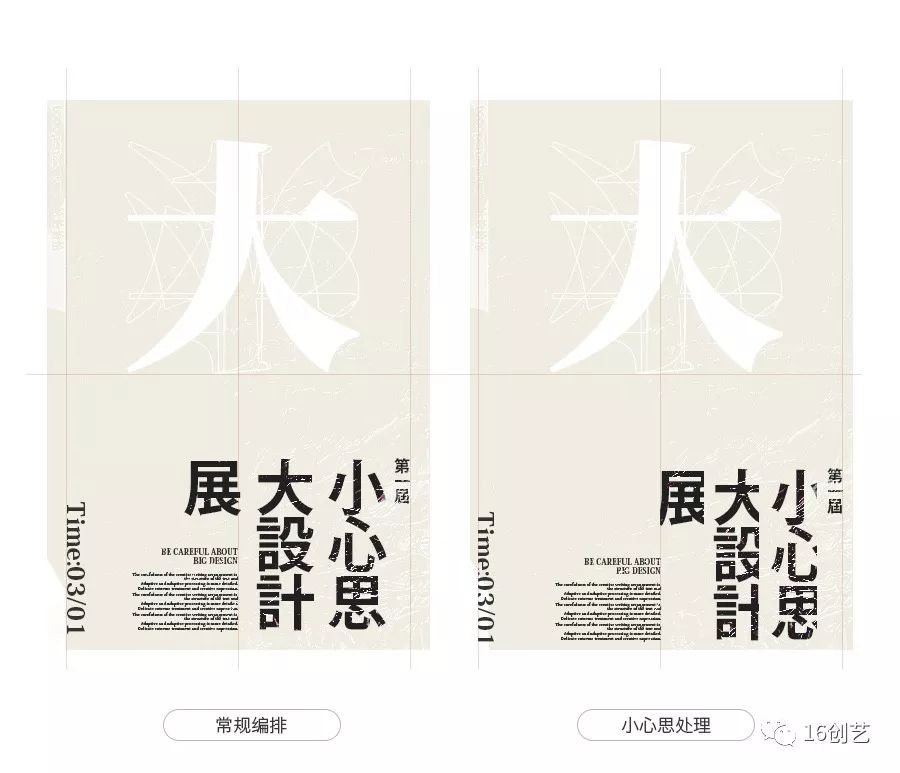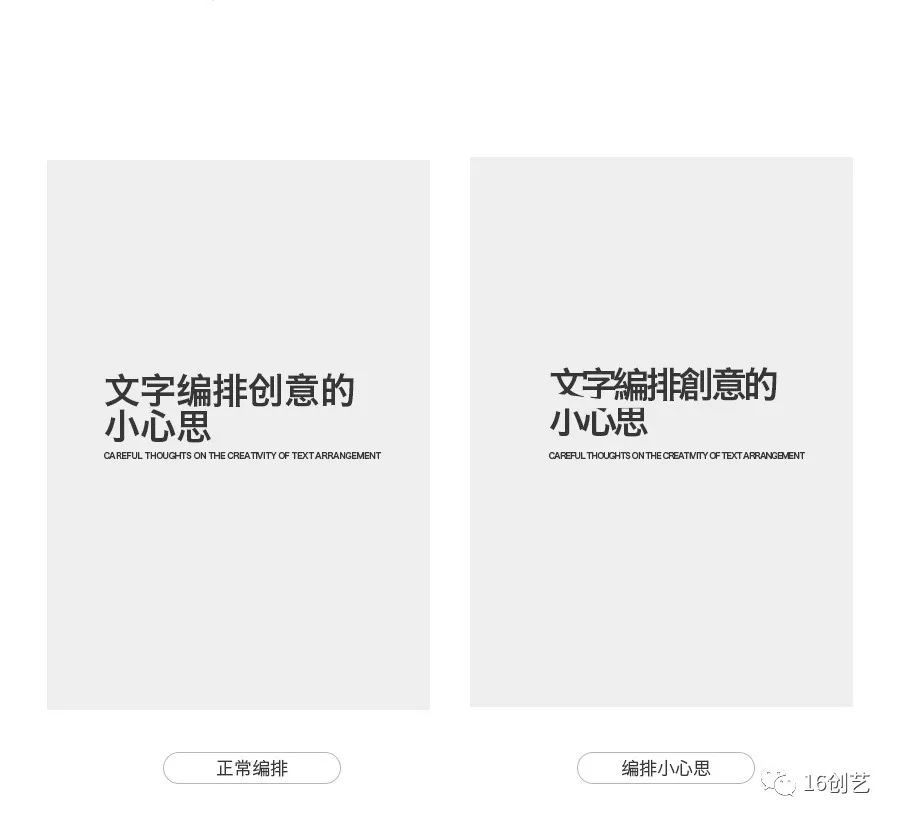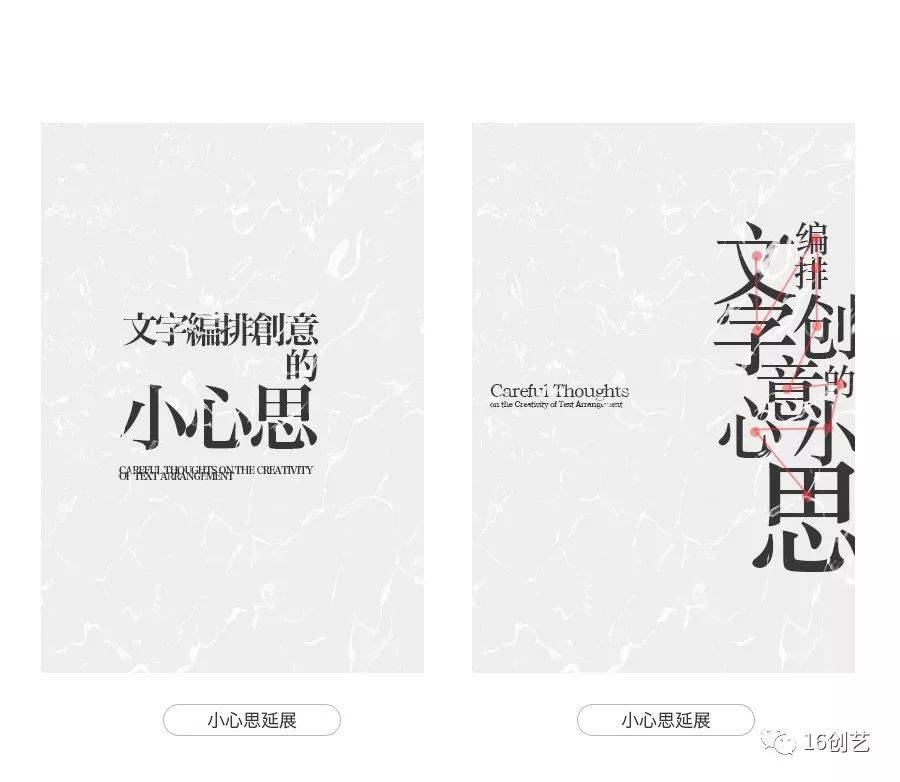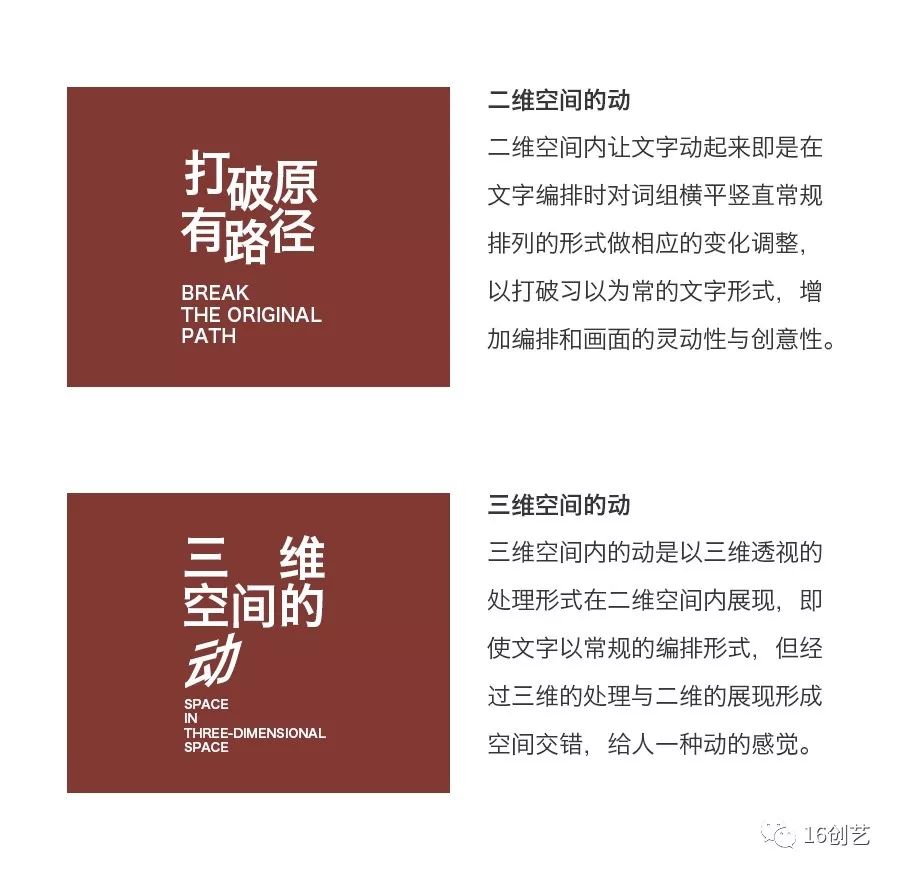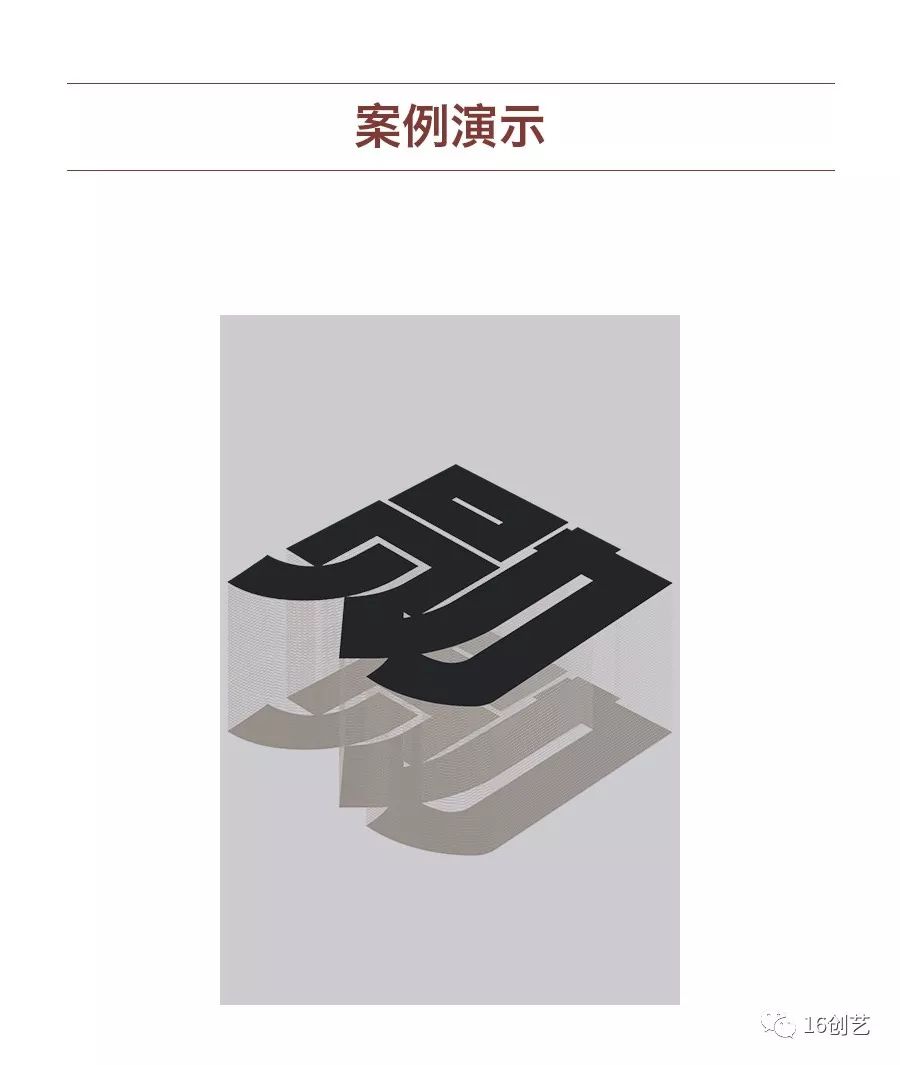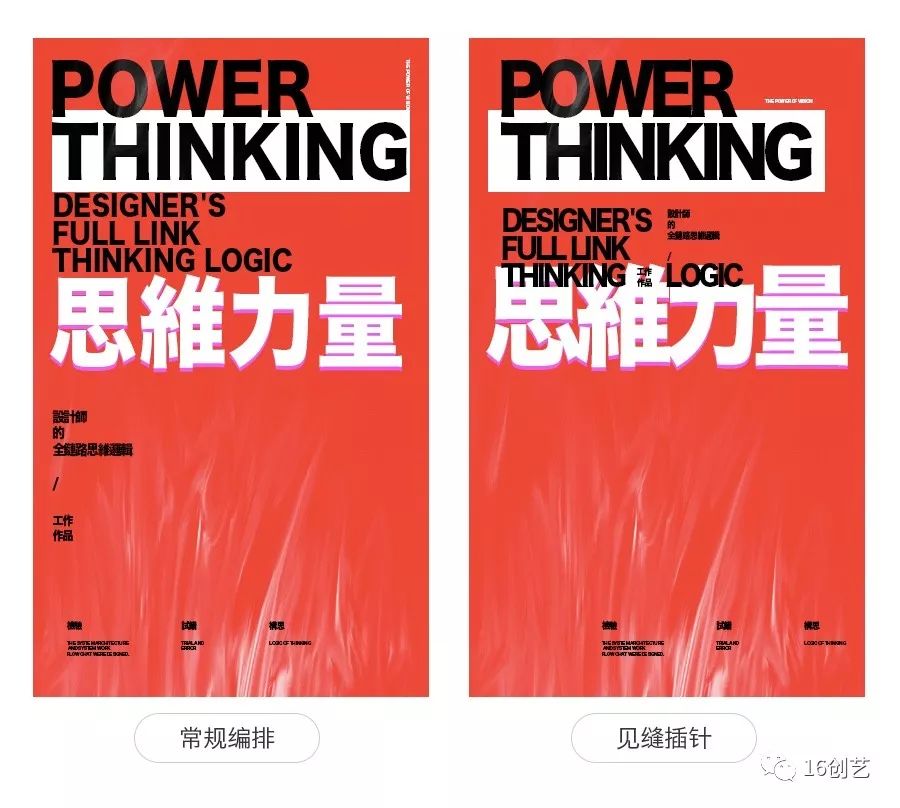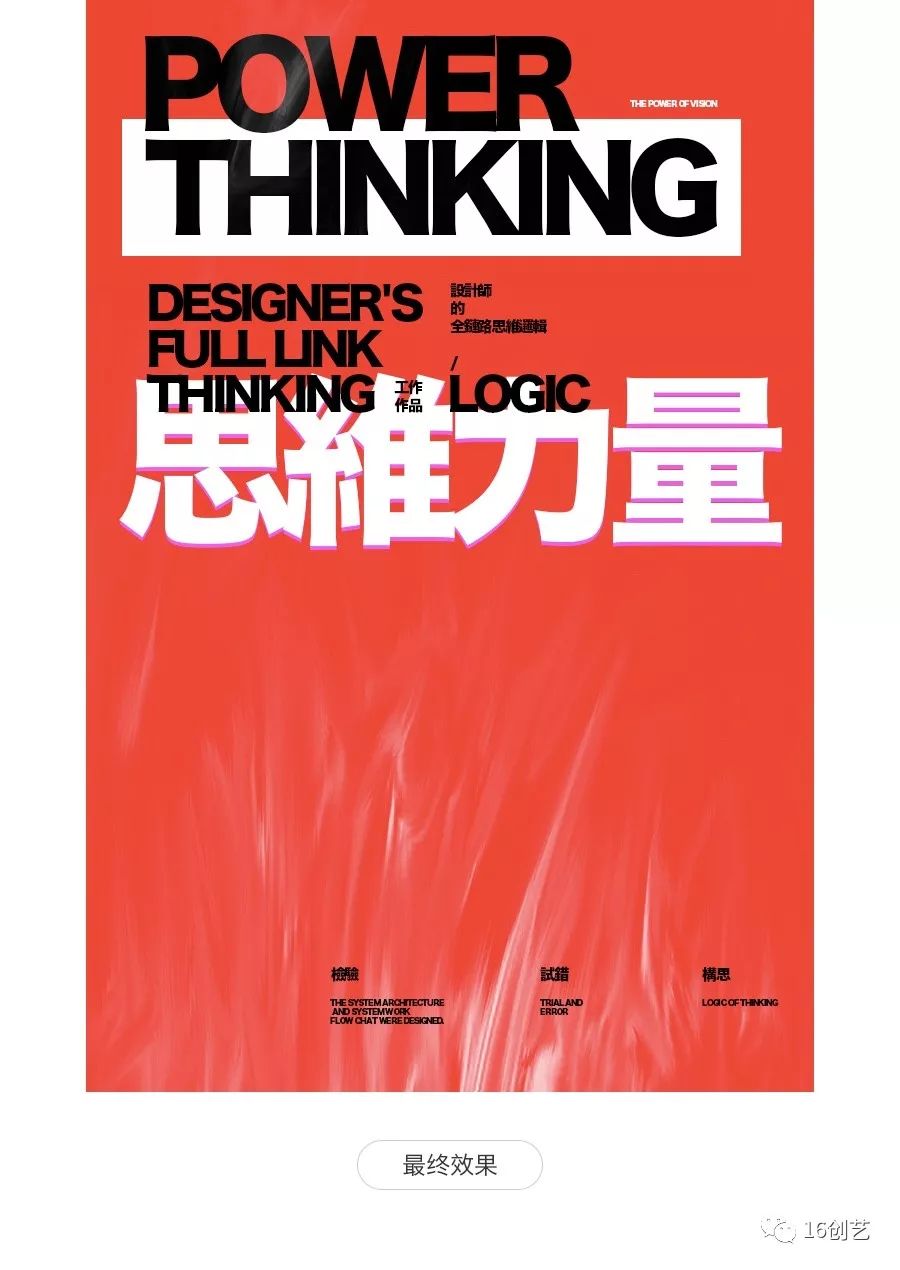
不会字体设计,不做视觉特效,也可以通过文字编排,让人眼前一亮
在设计中文字是很难避而不谈的话题,而作为设计师的我们大多数情况下也是在与文字打交道,其作为信息最重要的载体,不管是在网页设计中还是在平面设计中,为了可以更好的贴合主题,使信息准确有效的传递都需要对文字进行一定的处理,以具有美感的表现提升视觉感官对信息的接受能力,尤其是在信息繁杂的版式当中,除了字体设计能够提升文字编排的趣味性、创意性和独特性之外,在组合编排时还可以利用一些简单的,巧妙的处理手法提升文字自身的创意性和整体画面的视觉美感,本期文章将通过详细阐述文字编排进行创意表现处理时体现出的小心思,即使不会字体设计、不做视觉特效,如何使用常见的手法也可以给人眼前一亮的细腻感受。
文字编排创意是利用文字自身的结构和字形特点,通过对文字的自适应和它适应(不知道自适应和它适应的请翻看之前的文字编排文章)对整组或者单个文字使用一些设计中的表现手法营造打破文字常规输入排列的视觉创意,也是对文字应用的二次加工处理,以更好的贴合画面主体增强文字自身的表现力和承载信息的生动演绎,即使只是用字库现有的文字通过对文字编排进行小心思的处理,也可以为版式的信息编排提供富有创意性且具有美感的视觉表现。
图1:
文字在进行创作时均是按照一定的规范进行标准的输入,同时也是以直线的展现形式进行使用,不管是中文也好、英文也罢,在常规的编排使用时很难最大限度的满足设计师的创意需求,尤其是在有限的版面空间内,常规的输入很容易产生限制和呆板的印象。
图2:
在不改变文字编排形式的情况下,缩小文字的字间距和行间距使其更加紧凑的排列,同时
在对齐方向对行与行之间进行适当的截取处理,以呼应文字末尾自然形成的段落留白,而
截取形成的方向在视觉上也起到一定的阅读引导,先紧凑和后截取的小心思处理不仅让视
觉也更加集中,也文字编排具创意性。
图1:
而当换一种文字和方式进行编排,同样把文字的行间距和字间距进行缩小,中文并进行大小对比的处理后可以看出,文字整体在发挥自适应的同时以矩形编排给人一种规矩中带有变化的感觉,即保证文字信息有效传递和识别也突出主题,英文缩小行距之后产生了文字交叉,并且在交叉处形成了可视的线以小心思来体现文字编排的创意。
图2:
而要想在文字编排中加入小心思处理以突显创意性提升画面美感和设计感,还可以打乱文字原本的秩序重新建立新的秩序,利用文字自身的特点把常规展现的路徑打乱之后,使用凌乱美的表现手法重新建立阅读秩序进行编排,并适当的调整文字的大小以增强文字的表现力和创意性,在满足自适应的同时也能很好的体现出它适应以满足整体画面。
图1:
在常规的编排当中,文字信息以最基本的对齐方式有序的排列,看上去基本上没什么问题而很多时候也会以这种形式作为最终的设计稿,但却没有认真的考虑过文字笔画特点所产生的视觉影响,尤其是在使用两种不同类型文字编排中,笔画鲜明的特点与不同的结构会造成物理对齐后的视觉差,进而产生留白不均匀与重心不协调等问题影响画面视觉体验。
图2:
画面中主体为宋体类型的文字,而标题是黑体类型的文字,两者虽然可以形成鲜明的对比,但笔画特点不一致也会传递出不同的气质,把标题文字和左边的英文进行纵向切割的小心思处理,在规避笔画特点产生的视觉不对齐时并形成物理对齐线,同时也是强调文字对齐方式,两侧文字的切割给人一种向中间靠拢的感觉,并在文字气质上使其进行有效的统一。
通过延展可以看出,文字本身具有较强的灵活性和多变的特点,即使是利用同一种处理手法也会对文字产生不同的视觉效果,其主要是受文字的类型所影响。
文字的松与紧可以说是设计师在与文字打交道的过程中接触最多的、最为常见,也是经常会使用到的一种关系,对文字而言松紧关系最直观的体现则是在字间距和行间距上面,尤其是在使用字库文字时都是以默认的间距为基准对信息进行编排和创意的发挥,缺少对文字松紧关系深入的探究,进而失去更多尝试和发挥创意的空间,而文字编排的小心思即是除了对间距加以利用之外,更是对文字本身的笔画和结构进行深入的探究营造出别具一格的视觉效果,进而提升文字编排的创意性,促进画面的视觉的表现力。
文字的松不仅是在基于字库默认间距的情况下适当的把字间距或行间距拉大,也是对笔画和结构的巧妙拆解,利用笔画结构、词组和段落之间的联系,平衡画面重心并对有限的空间进行一定的划分,同时也是在以文字为基准搭建另一个操控性较强视觉框架空间,在遵循阅读视线的情况下提升美感。
图1:
在常规的文字编排中,不对间距和结构做任何的调整可以看出,作为视觉元素的文字并没有任何的亮点和心思在里面,很难表现出具有意境和创作者的思想特点,而对于整个版面的空间把控上也只是局限于文字的多少和大小上面。
图2:
而当把中文的字间距适当的拉大之后可以看出,在满足文字组自适应的同时也是基于整体画面很好的发挥出文字的它适应与其他视觉元素形成呼应的关系,即有效的平衡整体的画面和空间的有效利用,也是常规小心思的表现。
对于灵活性较强的文字来说,不管是单个文字或者是词组亦或者段落,都应该更好的发挥出自身的特性,而并不是抑制,在常规的编排情况下,利用文字自身的特点对笔画和结构深入挖掘,在保证自适应和它适应的同时结合巧妙的创意,把中文进行拆解并加以利用后可以看出,不管是对文字组自身的编排也好,亦或者是对整体画面来说,拆解后的文字很好的提升了整体画面的创意性,对中文而言需要注意上下结构和左右结构的文字特点。
文字的紧凑与松散是相对的,是让文字的笔画结构和间距的距离在基于默认值的情况下更加的紧密,在保证可阅读的情况下给人一种更加密集的视觉感受,不仅可以使较为灵活且分散的文字建立连贯性和整体感,紧凑处理后所留下的空间也是为文字的自适应做铺垫,对于提升画面的艺术感,增加视觉的感知面积有着莫大的帮助,但同时紧凑处理的小心思受文字自身特点影响和文字的它适应影响。
图1:
文字在编排的过程中使用默认的间距值时可以看出,文字在自然的排列下没有任何的节奏感和美感,即使在对整体的布局有严格的把控也没能对版面起到有利的视觉效果和创意,最终只能以简单的呈现表现。
图2:
在不改变整体的布局情况下,利用紧凑的小心思对文字进行适当的缩近,尽可能的去掉英文字母的行间距,使其在视觉上紧密相连,营造一条有形的线,同时对其他相应的文字也进行调整,不仅为画面增添创意性,也是对空间的重新划分。
另外还可以对文字进行“过分”的间距缩进,使其更加的紧密并形成一定的交叉,以突显艺术性,但需要注意文字的识别性与画面整体空间的划分。
在上篇文章中已经提高过小心思的扭转,对文字而言也是路径的一种的形态变化,文字的路径是以对齐的起点为基础按照直线的形式进行输入,具有强烈的、且较为固定的方向性,也是对阅读视线的引导,而文字编排即是对排列的编排和形态变化的探究,直线的变化有多少种,文字编排的路径就可以有多少种,而大多数情况下也只是使文字沿着常规输入的路径进行排列,而想要使文字编排具有创意性就需要使用小心思对路径变化进行探究,其常用的路径变化大致有以下几种。
路径的变化形式还是比较多的,这里大致列举6种常用的形式供大家参考,更重要的是要了解文字路径的变化形式同时在使用路径变化的小心思时需要注意整体版面的变化,只需要对整组文字种的个别词或者句子进行适当的调整即可增强文字编排的创意性。
图1:
在常规编排的情况下,如果主体元素比较具有特点或者比较突出,而文字组则可以以常规的编排形式贴合主体,给人一种简单安静的视觉感受,但如果感觉过于平淡则可以适当的利用文字的路径变化进行调整以作为画面的创意点。
图2:
在保持整体的画面的情况下对中文标题种的其中一个文字进行路径的反向变化处理在保证可识别的情况下,把从上向下一致的阅读视线利用反向的变化使其折回,在同一句文字中形成路径的交叉,作为编排的创意点丰富整体的画面。
而当把中文进行旋转的路径变化后可以看出,在体现小心思的同时也提升了画面的灵动性和创意性。
在上一篇小心思的文章中提到的方法同样适用于文字编排,但除此之外针对繁杂、枯燥而又灵活多变的文字来说,在结合自身的特点情况下也有符合文字专属的小心思处理,文字作为画面中较为重要的视觉元素,通常情况下对于小心思的使用并不局限于单个设计手法和技巧,在增加文字编排创意表现时不仅是对自身的特点深入的刻画,也是对画面整体视觉表现的把控,对文字而言,小心思的体现可以从2个基本的纬度着手。
文字通常给人的感觉是安静的、单一的、不管是对单个文字或者对词组句子来说都是如此,尤其是在使用字库文字进行编排时很大程度上受其输入路径的限制难以更好的满足创意想法,让文字动起来并不是把文字做动态的处理,而是打破原有的输入路径和文字编排常规的结构,也是让文字在静态呈现的状态下具有动态的感觉,实现动中有静的视觉效果,除了上篇文章中提到的旋转方向,还有更多的小心思可以实现让文字在静态中动起来的目的。
新建一个画布,把主体置入到版面当中并调整到合适的位置,然后思考整体版面展现形式以及最终的视觉呈现效果,对于立体的主体来说本身已经已经具有强烈的空间感,并给人一种动的感觉,通常情况下文字编排的置入基本上是以静的形式。
图1:
对画面进行适当的修饰和效果的处理以更好的满足我们想要的效果,然后把所有的文字置入到画面中进行编排,在常规的编排下文字信息只单纯的排列和画面的空间填充,不仅文字自身没有创意性和美感,也没有对画面起到太多的气质和视觉刻画。
图2:
当结合画面整体所表达的气质对文字组其中的一个词以三维空间的动透视的处理,在保证自适应的情况下,使文字有一种空间的延伸感,并加入波纹的处理以贴合画面的效果,在提升自身创意的同时更好的满足于整体画面的视觉美感。
另外,不管是单独的文字编排亦或者在整体画面中的应用加入小心思后的文字编排更加的具有美感,同时也为画面增添了一定的创意性。
见缝插针也是文字编排的过程中经常会用到的一种设计手法,是对文字结构和空间利用最有效的编排形式,也是对文字大小对比关系的另一种诠释很多情况下在进行文字编排时为了更好的有效利用版面空间或者使文字编排具有强烈的稳定性都会用到这种小心思,而在使用字库文字受限的情况下却不能更好的利用这种小心营造具有一定的创意的文字编排来丰富整体的画面。
新建一个画布以纯文字作为画面的主要表现强调文字本身所要表达的内容,凸显文字本身的创意性,并置入一个肌理的图片以表达思想的缜密。
图1:
对肌理进行适当的调整以贴合想要表达的效果,同时置入文字并在版面空间内适当调整以达到合理的使用,在正常的编排情况下文字编排虽然对空间的使用比较合理看起来也没什么问题,但就是感觉不够精致没有太多的特别之处。
图2:
而当文字进行编排时结合见缝插针的小心思对其重新考量,并对文字的间距进行调整之后可以看出,在保证文字信息有效传递的同时,使文字与文字之间比较巧妙的组合在了一起,给人一种精致的视觉感受,即使没有视觉突出的主体也可以很耐看。
文字作为设计中必不可少的视觉元素,其自身的繁杂也是一致困扰设计师的问题,不管是字形设计也好、编排设计亦或者是字效设计都是非常值得细心深入探究与不断尝试的一个分支,而对于文字编排来说想要表达出创意更多的是对结构和空间的把控,看似不起眼的小心思经过反复推敲之后就会有不一样的视觉效果和收获。